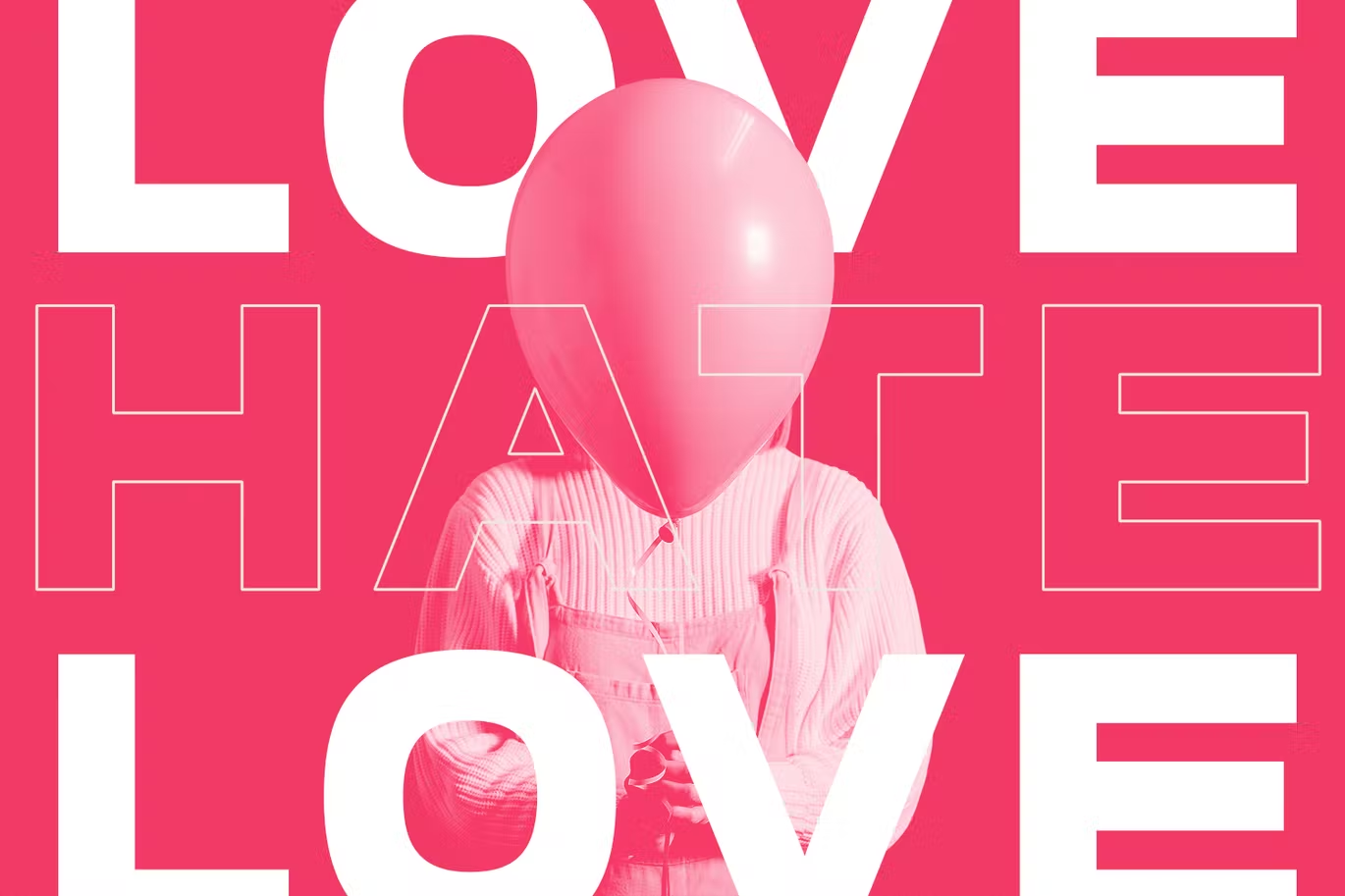
Komrad Sans Display Font
Description de Komrad Sans Display Font
Komrad est une police moderne sans empattement, entièrement en majuscules. Avec un trait semi-gras, un caractère amusant avec un peu de ligatures et d’alternances. Pour vous offrir un travail créatif supplémentaire. La police Komrad prend en charge plus de 100 langues multilingues. Cette police convient à la création de logos, aux médias sociaux, aux titres de films, aux titres de livres, à un texte court, voire à une longue lettre de texte, et convient à votre police de texte secondaire avec sans ou empattement. Réalisez un travail époustouflant avec la police Komrad.